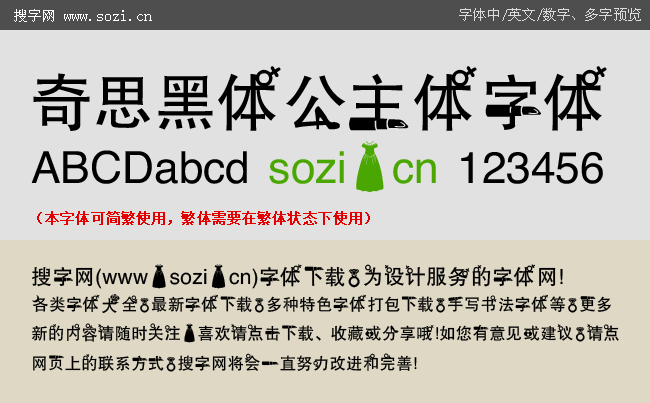
奇思黑體公主體字體
搜字網(wǎng)給大家提供一款奇思黑體公主體字體手機(jī)中文字體下載。這款手機(jī)字體是以黑體字體為原形,在字體間嵌入卡通圖案。標(biāo)點(diǎn)也換成了卡通圖案,具有黑體端正易認(rèn)的風(fēng)格,又很有趣味性,特別適合喜歡手機(jī)字體個(gè)性一些的朋友在手機(jī)上安裝使用。